Вариативные шрифты: возможности, преимущества и ограничения
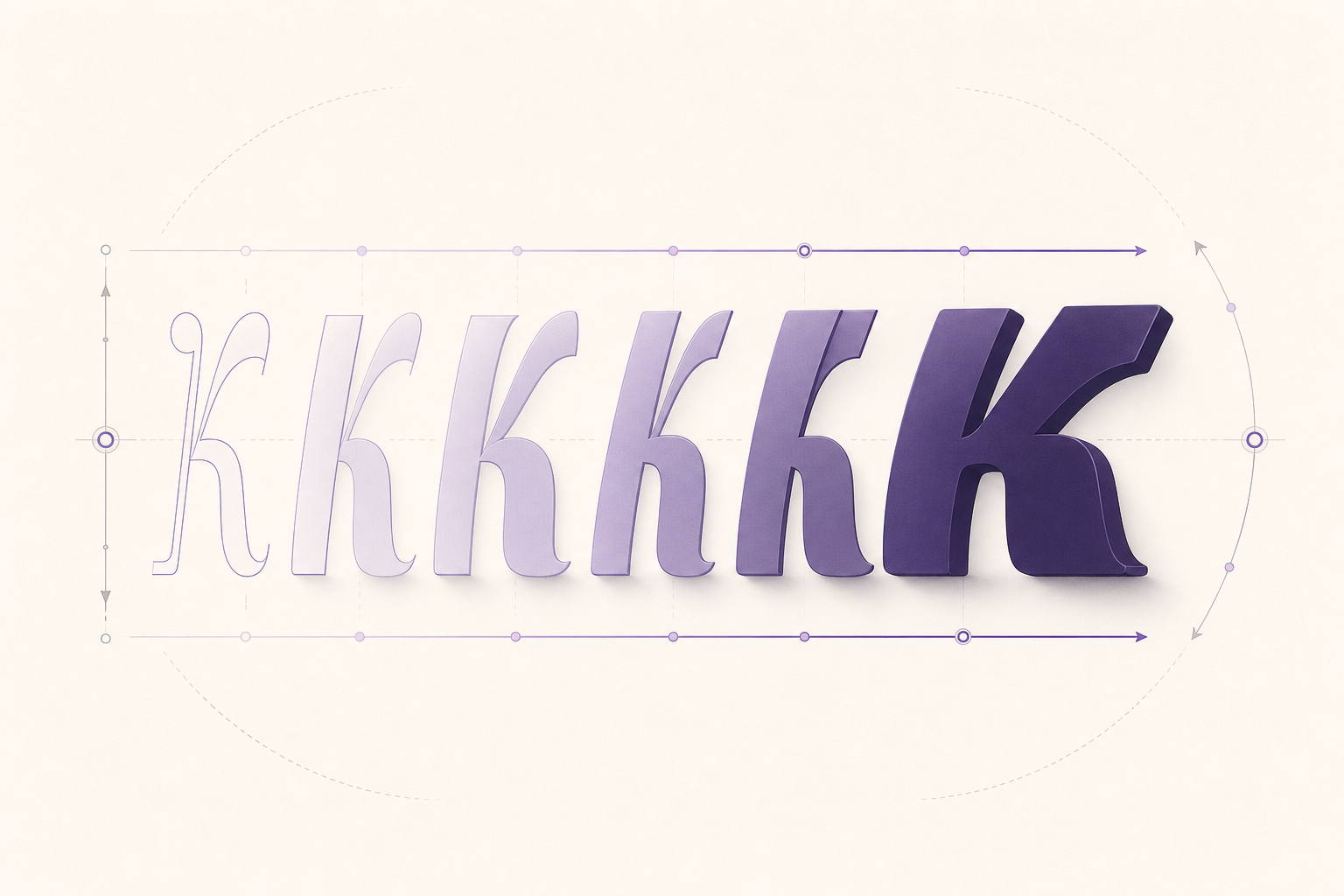
Вариативные шрифты: что это и зачем они нужны
Вариативный шрифт — это один файл, внутри которого хранится диапазон начертаний: от тонкого до жирного, от узкого до широкого и от прямого до наклонного. Вместо отдельного файла для каждого начертания дизайнер получает управляемую систему параметров. В статье разберём устройство variable fonts, их пользу для веба и ограничения при создании и использовании.
Как устроен variable font
Обычный шрифт состоит из отдельных статических файлов: например, Regular, Medium, Bold и Italic. Вариативный шрифт объединяет такие параметры в единую интерполируемую модель. Пользователь или CSS задаёт значение оси, а приложение вычисляет промежуточное начертание. Поэтому между Regular и Bold можно выбрать не только готовую ступень, но и любое допустимое значение насыщенности.
В основе технологии лежат таблицы OpenType и оси вариаций. Стандартная ось wght отвечает за толщину, wdth — за ширину, slnt — за наклон, ital — за наличие курсивного стиля, а opsz — за оптический размер. Автор шрифта может добавить пользовательские оси, например контраст штрихов, округлость форм или степень декоративности. Названия и диапазоны осей зависят от конкретного шрифта.
Стандартные и пользовательские оси
Стандартные оси проще использовать в разных программах, потому что приложения чаще распознают их автоматически. Пользовательские оси дают больше выразительности, но требуют документации и дополнительной проверки. Если дизайнер меняет нестандартный параметр, интерфейс редактора может показывать его неочевидно или вовсе не предоставлять к нему доступ.
- wght регулирует толщину знаков в заданном диапазоне.
- wdth меняет ширину шрифта без переключения на отдельное семейство.
- slnt задаёт наклон прямого начертания.
- ital переключает или описывает курсивную вариацию.
- opsz помогает адаптировать рисунок букв к размеру текста.
- Пользовательские оси управляют авторскими характеристиками конкретного шрифта.
Преимущества вариативных шрифтов для дизайна
Главное преимущество вариативного шрифта — гибкость. Дизайнер может точнее настроить иерархию, плотность набора и ритм текста, не ограничиваясь четырьмя или шестью статическими начертаниями. Это особенно заметно в интерфейсах, где один шрифт должен работать в заголовке, подписи, кнопке и длинном описании.
Более точная типографическая иерархия
Стандартного набора Regular, Medium и Bold иногда недостаточно. Например, заголовку может подойти значение толщины 620, а подписи — 470. Такие промежуточные настройки позволяют отделить уровни интерфейса мягче, чем резкое переключение между готовыми файлами. При этом важно сохранять визуальную последовательность: каждое значение должно быть проверено на читаемость и контраст.
Экономия файлов в веб-проекте
Один файл может заменить несколько отдельных файлов, если проект использует разные значения одной или нескольких осей. Это упрощает подключение гарнитуры, уменьшает количество запросов к серверу и делает систему шрифтов понятнее для разработчика. Однако размер самого файла и объём поддерживаемых символов всё равно имеют значение: вариативный формат не гарантирует автоматическое уменьшение веса.
Адаптация к разным экранам и сценариям
На узком экране можно немного уменьшить ширину букв, чтобы заголовок не занимал лишнюю строку. В крупном заголовке допустимо увеличить толщину, а в компактной подписи — выбрать более спокойное начертание. Такие изменения полезны для адаптивной типографики, но их следует применять осознанно: чрезмерное сжатие ухудшает форму букв и снижает комфорт чтения.
Выразительность в брендинге и motion-дизайне
Вариативные шрифты подходят для фирменных систем, где типографика должна реагировать на контекст. Логотипная надпись может быть широкой на обложке и более компактной в навигации, а в анимации начертание может плавно переходить от лёгкого к насыщенному. Такой приём создаёт динамику без замены отдельных изображений или текстовых слоёв.
Практические примеры использования
Рассмотрим несколько типовых сценариев. В интернет-магазине вариативная ширина помогает удержать короткие названия товаров в одной строке, если дизайн допускает небольшое изменение плотности. В финансовом интерфейсе разные значения толщины могут разделить суммы, подписи и второстепенные пояснения. В редакционном проекте ось оптического размера помогает согласовать крупные заголовки и мелкий текст.
- Определите диапазоны: для заголовков используйте выразительные значения, а для основного текста — спокойные и устойчивые к долгому чтению.
- Проверьте кириллицу: буквы должны сохранять единый характер, правильные пропорции и различимость в малом кегле.
- Сравните строки: протестируйте длинные предложения, числа, даты, кавычки и знаки препинания, а не только отдельные слова.
- Настройте адаптивность: меняйте параметры на контрольных ширинах экрана только там, где это решает конкретную композиционную задачу.